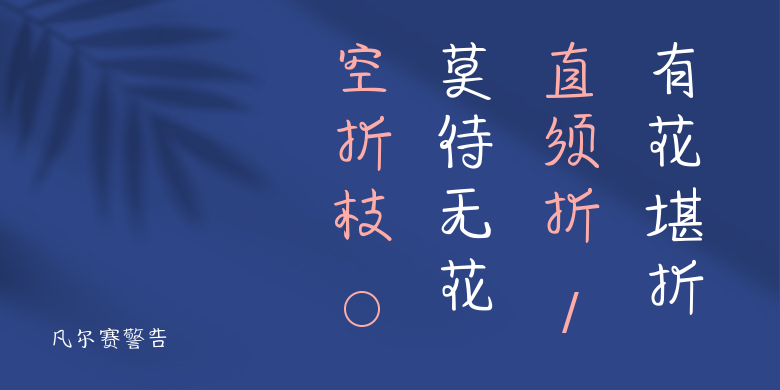
凡尔赛警告
凡尔赛警告,这款字体结构工整、笔画清晰,兼顾美观与易读性,适用于标题、正文、海报、包装、LOGO 等多种场景。字形优雅稳定,风格百搭耐看,适配日常排版与创意设计,让文字呈现更舒适、更具质感。凡尔赛警告一笔一画,皆是细节,以均衡的比例、流畅的线条打造舒适视觉体验,字形端正大气,风格简约现代。无论是商业设计、品牌宣传还是日常排版,都能轻松驾驭,让文字更有格调与力量。凡尔赛警告字体下载。